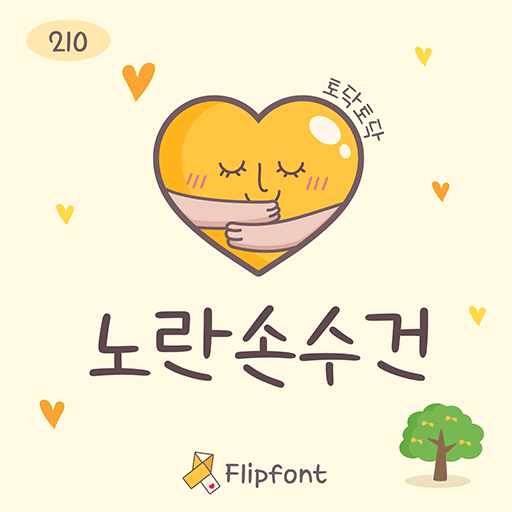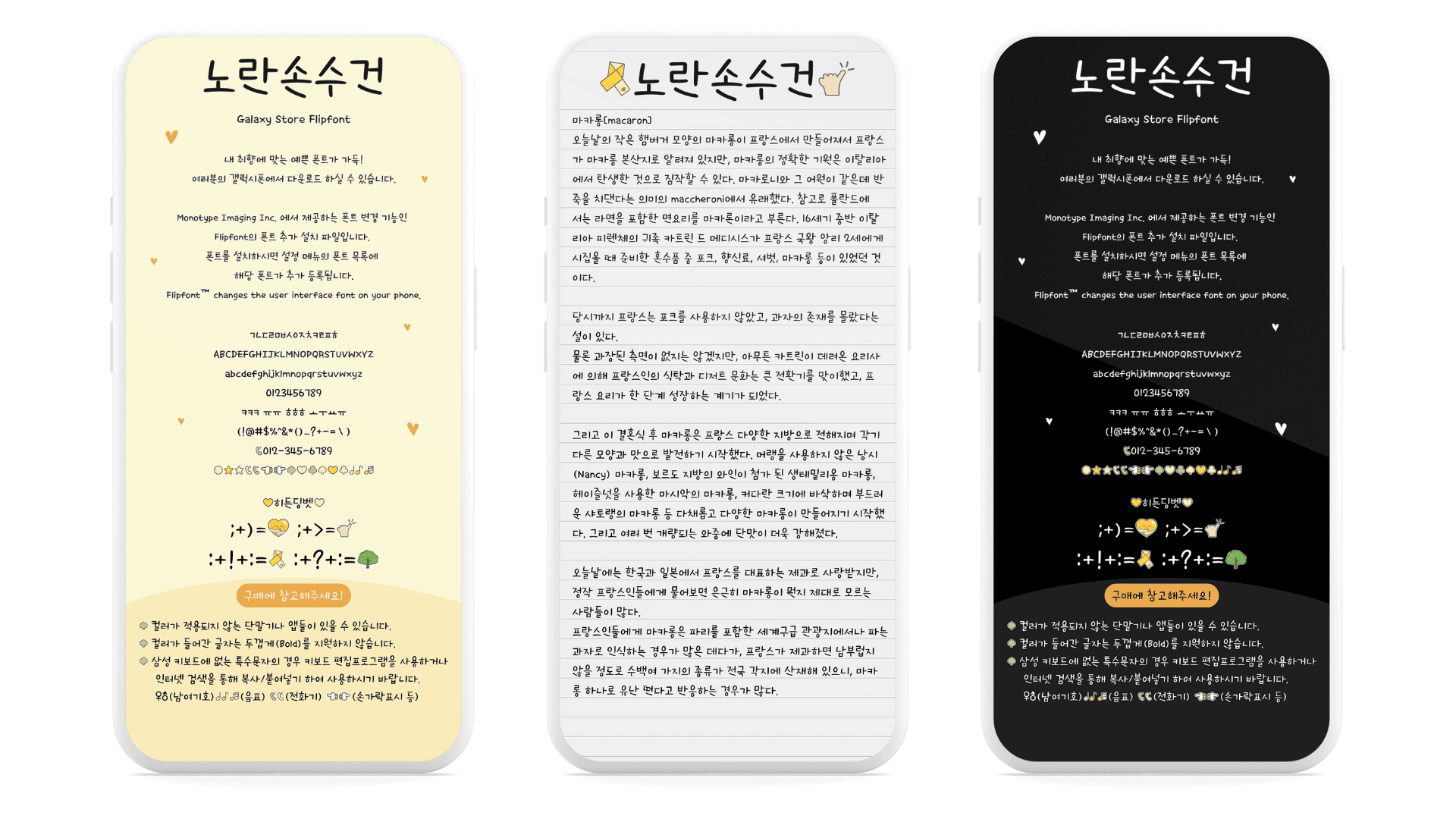
마음을 전할때 건네던 노란손수건 한 장을 폰트에 담아냈어요. 때때로 말 한 마디보다 건네는 손수건 한장이 더 위로가 될 때가 있어요. 순수하지만 성숙한 마음이 담긴 210 노란손수건 폰트를 만나보세요. 어른스러운 펜글씨 느낌의 폰트랍니다. 기존의 210노란손수건보다 가독성도 올라갔고 컬러딩벳도 추가되었어요!